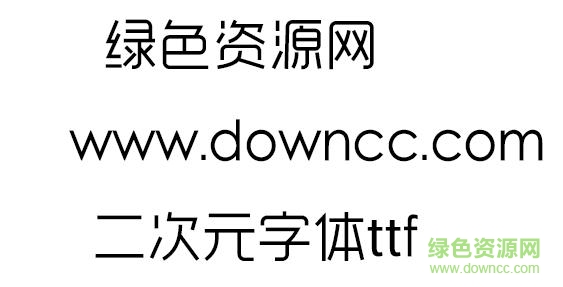
二次元字體ttf是一款最美的混搭二次元字體,讓你在使用的時候能夠感受到濃厚的二次元氣息,從而在二次元中進行文字輸入以及藝術(shù)字制作,讓二次元的小伙伴們都感受到最佳的字體視覺體驗,快來綠色資源網(wǎng)下載吧!
這款字體在二次元中十分流行,我就是通過二次元小伙伴推薦的,十分的好看,它的字體樣式十分規(guī)整,同時也透著俏皮的特色,我很喜歡!